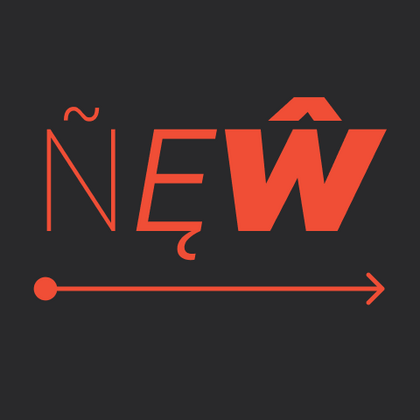
TT Regins — ТТ Реджинс
Произносится «ТТ Реджинс». «Regins» — производное слово от reign, в переводе с английского «царствовать». Буквы «TT» являются аббревиатурой названия компании
TT Quaris — ТТ Кварис
Произносится «ТТ Кварис». «Quaris» — искусственно образованное слово от латинского «quartz» (кварц), и своим названием намекает на драгоценные камни. Буквы «TT» являются аббревиатурой названия компании.
TT Bakers — ТТ Бэйкерс
Произносится «ТТ Бэйкерс». «Bakers» — производное слово от baker, в переводе с английского «пекарь». Буквы «TT» являются аббревиатурой названия компании.
TT Neoris — ТТ Неорис
Произносится «ТТ Неорис». «Neoris» — производное слово от neo («новый» с латинского) и rise («восход» с английского). Буквы «TT» являются аббревиатурой названия компании.
TT Marks — ТТ Маркс
Произносится «ТТ Маркс». «Marks» — множественное число мужского имени Mark. Шрифт назван в честь сына соавтора шрифта. Буквы «TT» являются аббревиатурой названия компании.
TT Disruptors — ТТ Дизрапторс
Произносится «ТТ Дизрапторс». «Disruptors» — производное слово от disrupt, в переводе с английского «разрушать». Буквы «TT» являются аббревиатурой названия компании.
TT Gentlemens — ТТ Джентльменс
Произносится «ТТ Джентльменс». «Gentlemens» — производное слово от Gentlemen, в переводе с английского «джентельмены». Буквы «TT» являются аббревиатурой названия компании.
TT Gertika — ТТ Гертика
Произносится «ТТ Гертика». Слово «Gertika» является неологизмом. Буквы «TT» являются аббревиатурой названия компании.
TT Biersal — ТТ Бьерсал
Произносится «ТТ Бьерсал». «Biersal» образовано от немецкого Bieresel — имени домашнего духа из мифологии. Буквы «TT» являются аббревиатурой названия компании.
TT Paplane — ТТ Паплэйн
Произносится «ТТ Паплэйн». «Paplane» — производное слово от paper (с английского «бумага») и plane (с английского «самолёт»). Буквы «TT» являются аббревиатурой названия компании.
TT Travels Text — ТТ Травелс Текст
Произносится «ТТ Травелс Текст». «Travels» — производное слово от travel, в переводе с английского «путешествие», «Text» — в переводе с английского «текст». Буквы «TT» являются аббревиатурой названия компании.
TT Carvist — ТТ Карвист
Произносится «ТТ Карвист». «Carvist» — производное слово от carving, в переводе с английского «вырезание». Буквы «TT» являются аббревиатурой названия компании.
TypeType представляет новую коллекцию шрифтов — свежие и современные гарнитуры, разработанные с учетом последних тенденций типографики. Эти новые шрифты сочетают оригинальный дизайн с практичностью: они отлично подходят для цифровых проектов, брендинга и печатных материалов. Каждая гарнитура проходит тщательное тестирование, чтобы обеспечить удобочитаемость и стильное исполнение.
Обновление библиотеки TypeType — это всегда новые возможности для дизайнеров, которые хотят выделиться.